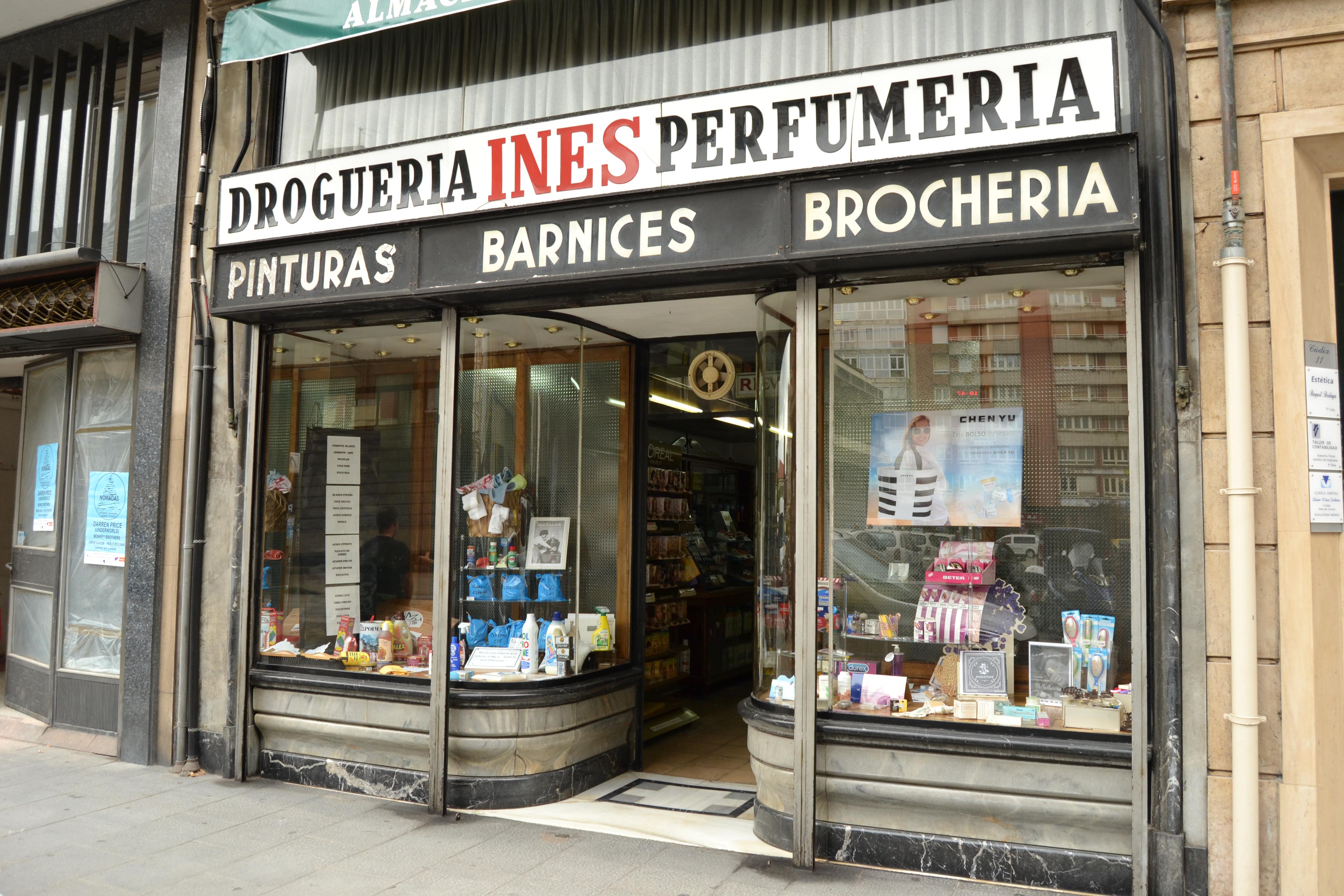
El paso del tiempo
Entre estas dos fotos hay más de 50 años de diferencia, todo ha cambiado excepto una cosa: Droguería Inés. Es increíble ver como un negocio se mantiene intacto y con su propia personalidad al margen de modas de diseño, la irrupción de las grandes marcas o que una calle entera cambie.
Así quien quiera darse una vuelta por el Santander de los años 50, lo tiene bien fácil. Ahora, si encima os invitan a ver la trastienda, la experiencia puede ser preciosa porque veréis cosas que ya ni existen ????
Droguería Inés, años 50. (Foto cedida por Javier Velasco)